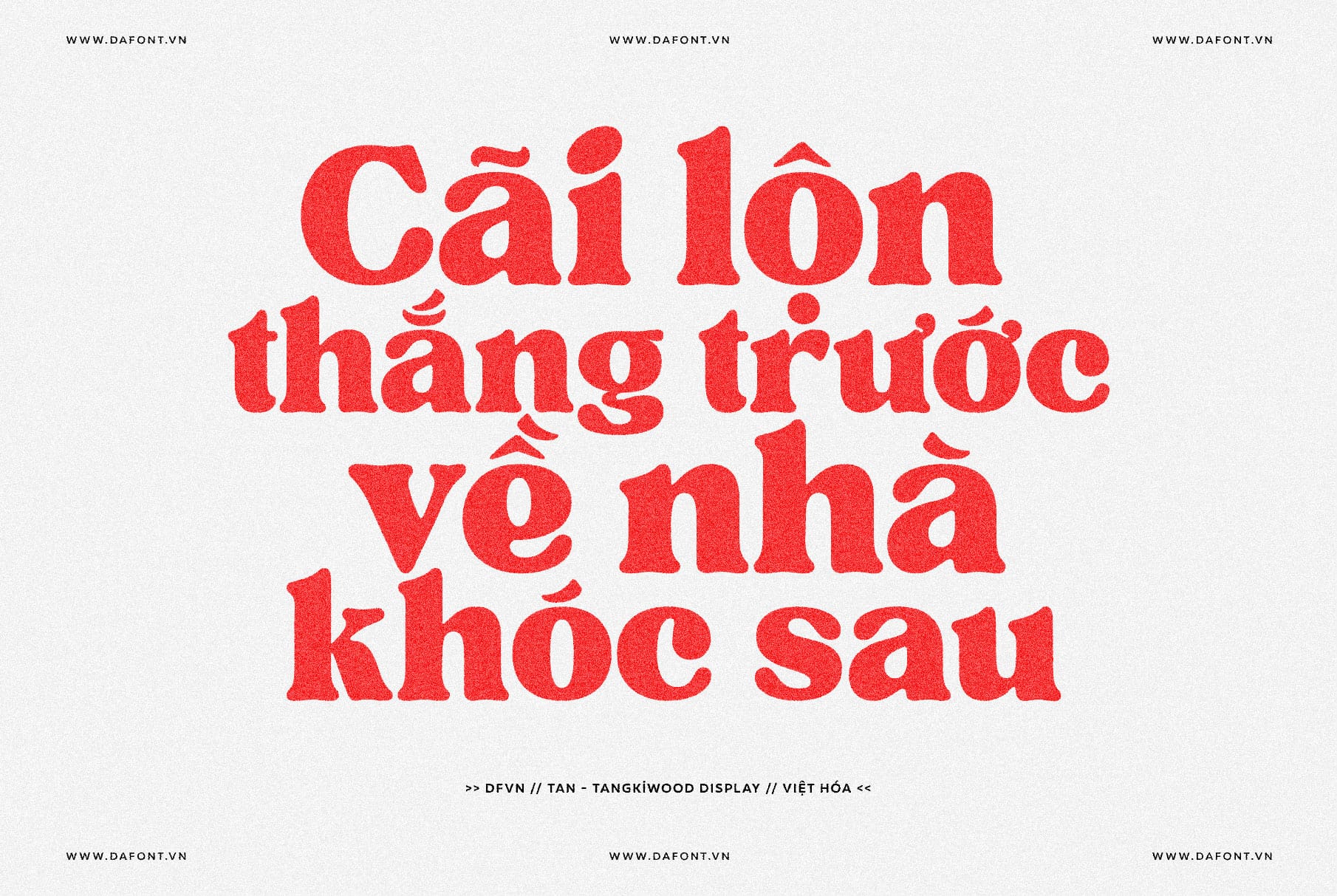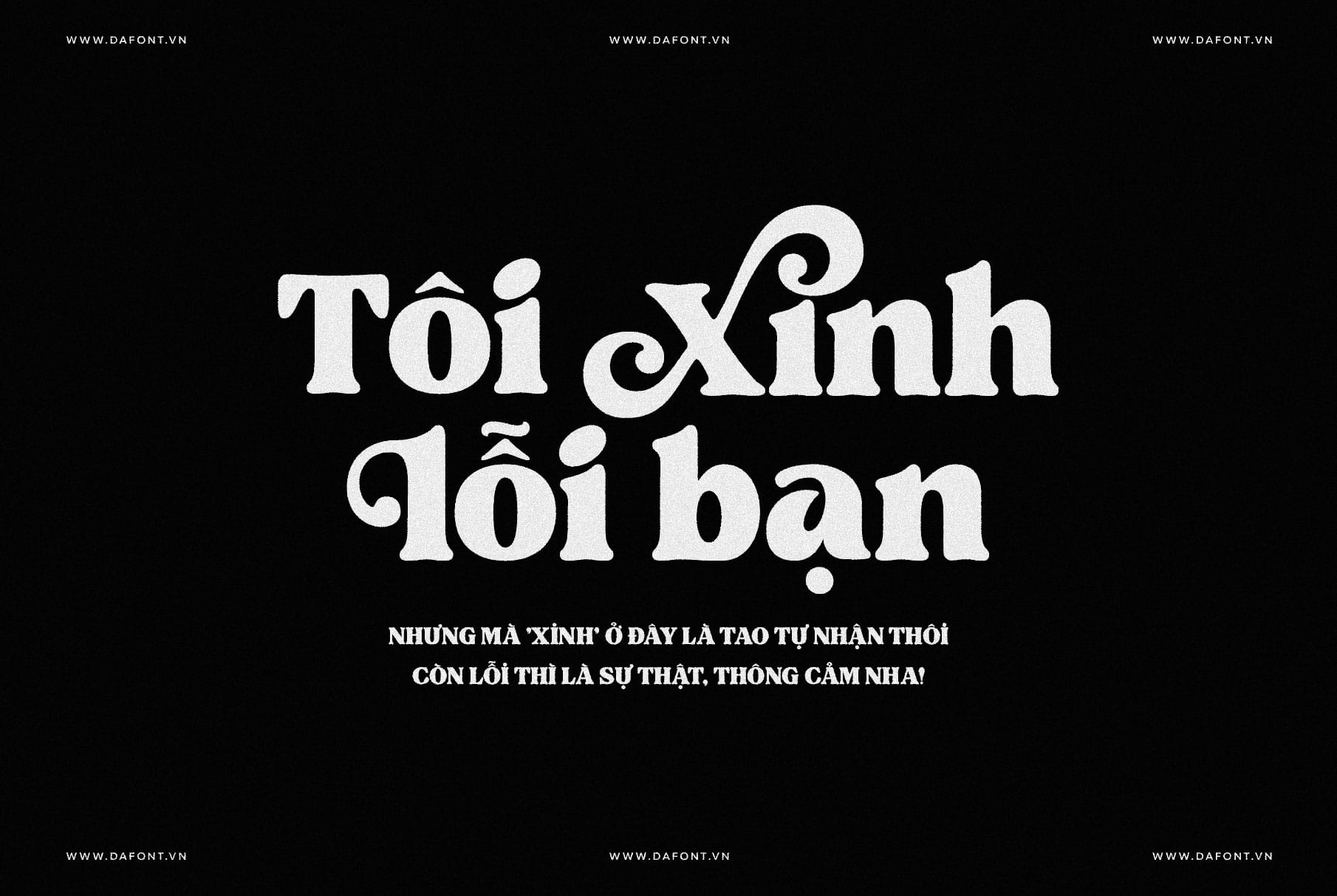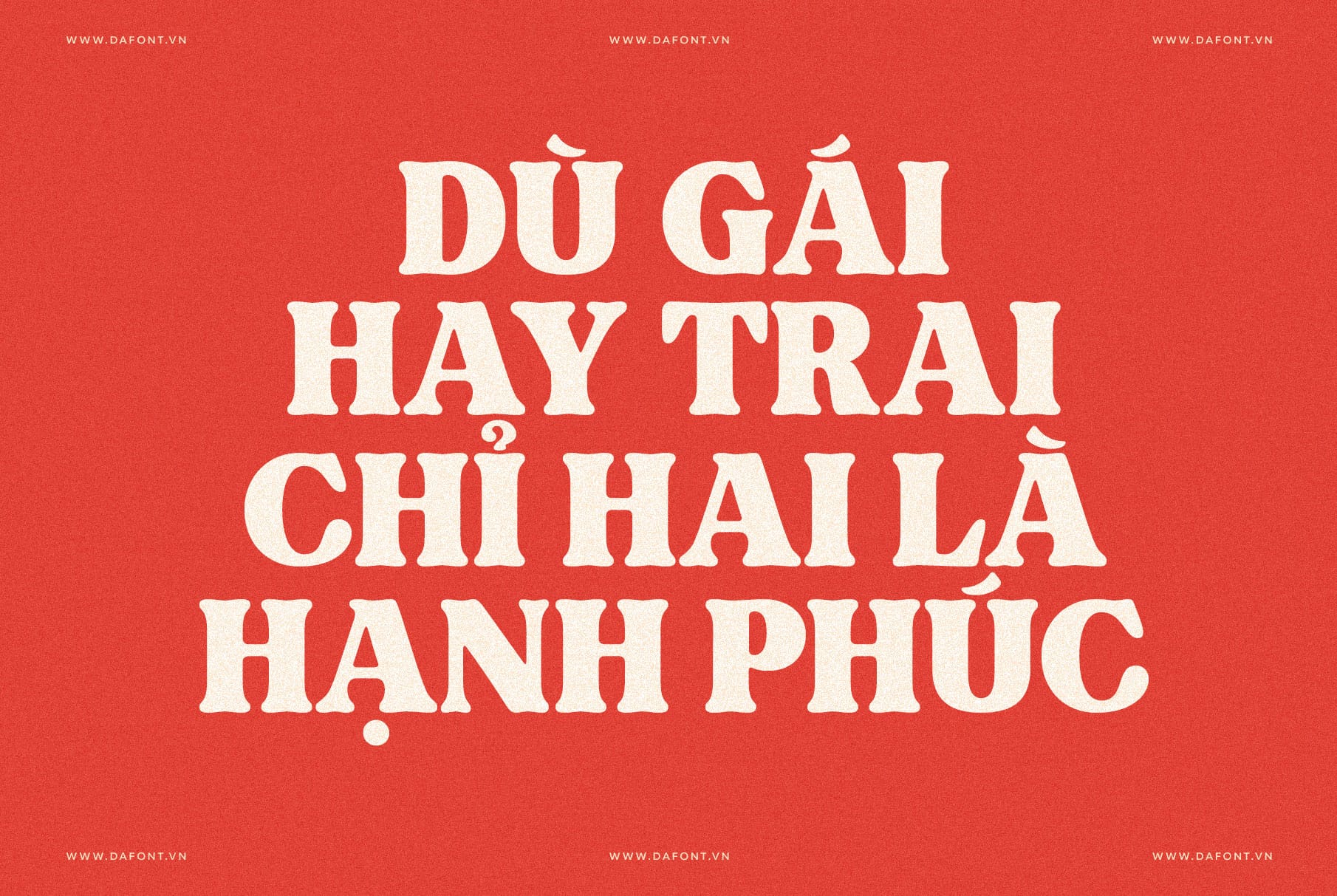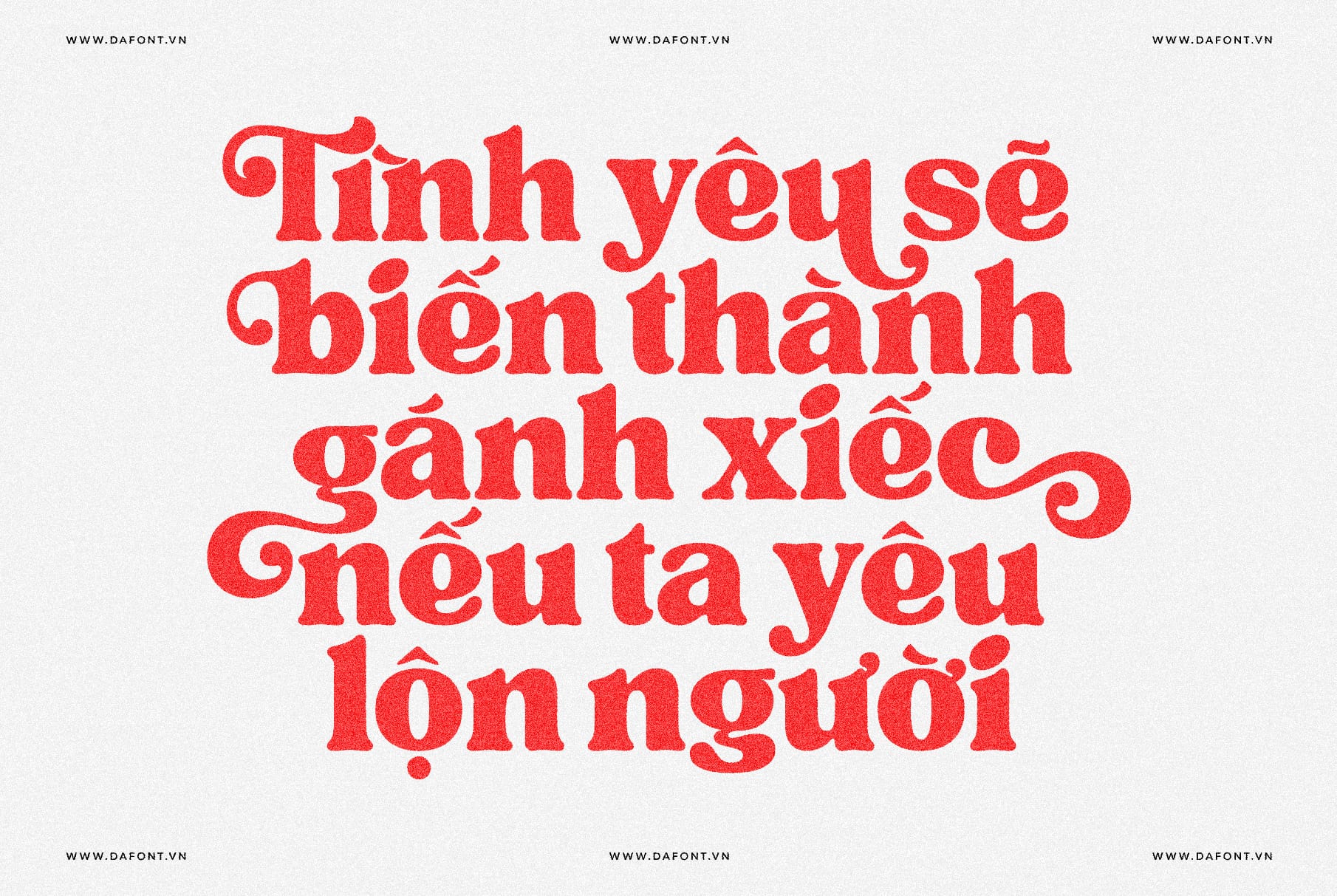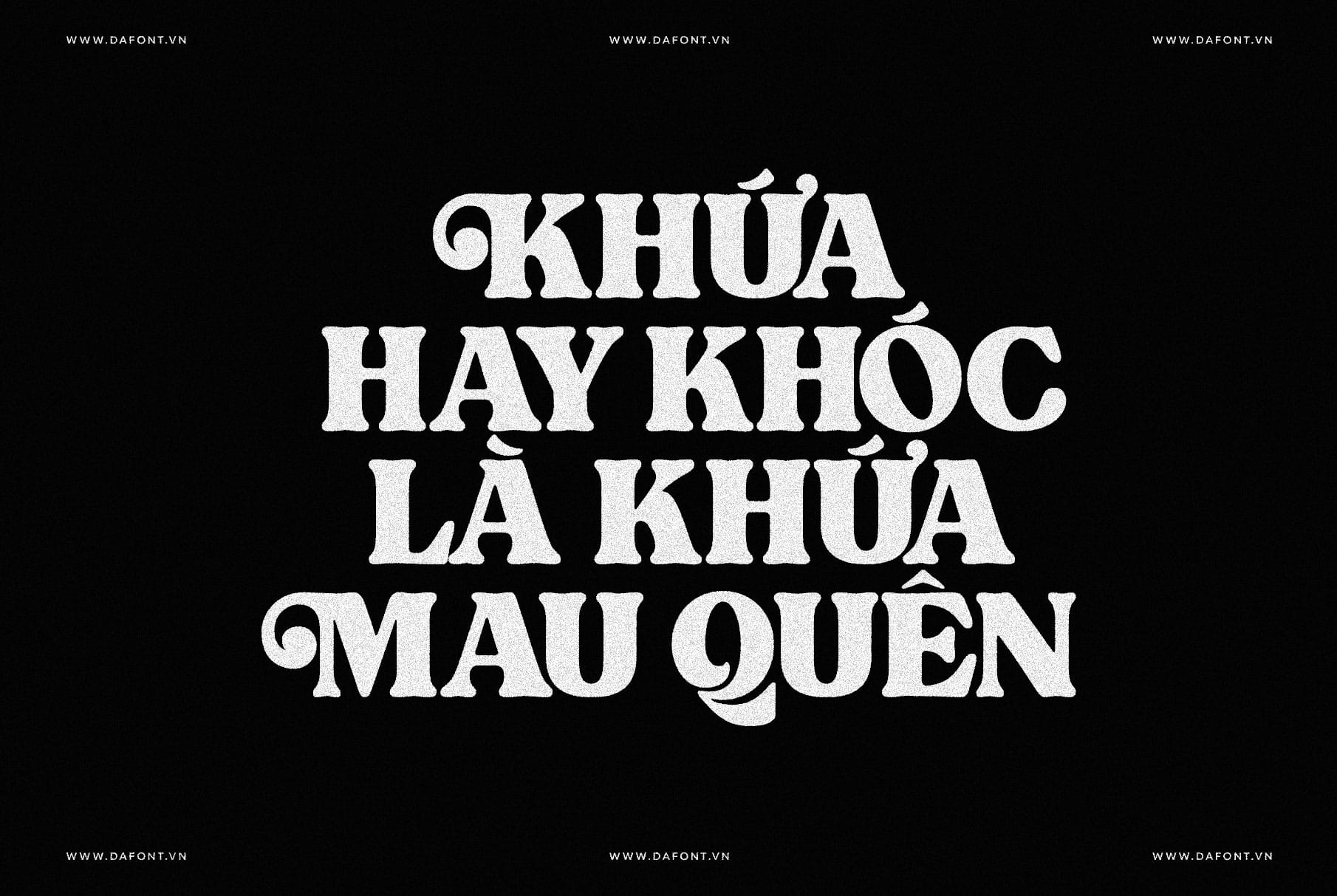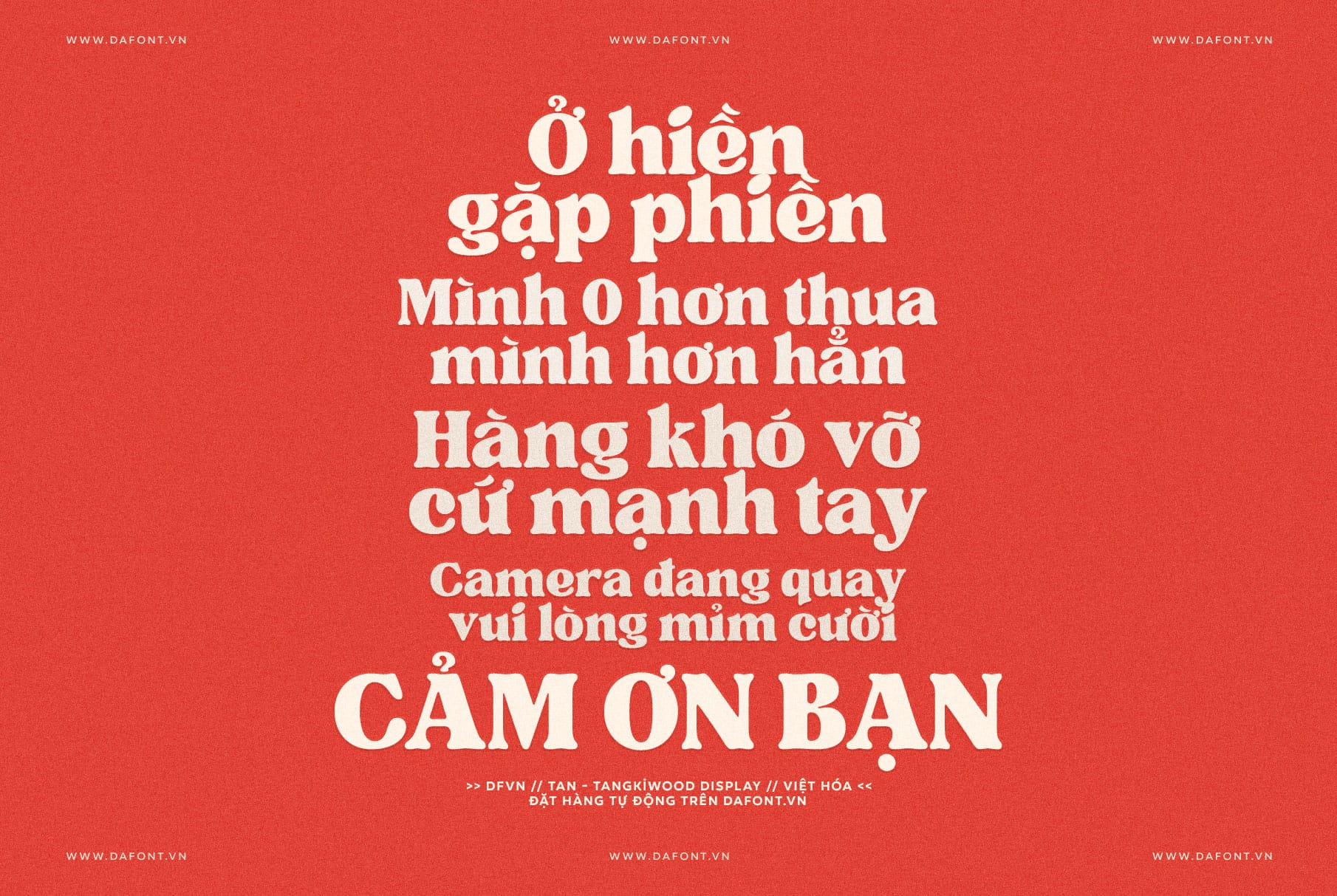
DFVN TAN – TANGKIWOOD
Phong cách retro đậm chất 70s cho thiết kế hiện đại
Nếu bạn đang tìm kiếm một font chữ có khả năng thể hiện đúng tinh thần của một thời đại hay một cảm xúc cụ thể cho thiết kế của bạn. DFVN TAN – TANGKIWOOD chính là một typeface dành cho bạn, mang đậm dấu ấn của thập niên 70 với vibe retro độc đáo, đồng thời sở hữu sự mạnh mẽ và vui tươi.
DFVN TAN – TANGKIWOOD – Đậm chất retro
Angkiwood là một display typeface với một độ đậm duy nhất, được thiết kế lấy cảm hứng từ phong cách thập niên 70. Với vibe đậm chất retro, font chữ này mang đến sự kết hợp hoàn hảo giữa sự táo bạo và vui nhộn, làm cho nó trở thành một serif typeface thú vị.
DFVN TAN – TANGKIWOOD không chỉ nổi bật với các đặc điểm thiết kế độc đáo mà còn cung cấp các alternates (ký tự thay thế) cho cả chữ hoa và chữ thường, giúp tăng thêm sự đa dạng và cá tính cho văn bản. Ngoài ra, với hơn 500 ký tự thay thế đã được Việt hóa và dễ dàng sử dụng bằng tính năng Opentype.
Ứng dụng lý tưởng của DFVN TAN – TANGKIWOOD
Với kiểu chữ hiển thị và cảm hứng cổ điển, Angkiwood phù hợp cho nhiều mục đích sử dụng:
• Tiêu đề và tựa đề: Làm nổi bật tiêu đề trên trang web, blog hoặc tạp chí với phong cách bắt mắt.
• Áp phích và tờ rơi: Hoàn hảo cho các sự kiện quảng bá, đặc biệt là những sự kiện mang chủ đề âm nhạc hoặc cổ điển.
• Thương hiệu và logo: Tạo ra những logo đáng nhớ cho các thương hiệu muốn gợi lên sự hoài niệm hoặc hình ảnh vui tươi.
• Thiết kế bao bì: Thêm nét quyến rũ cổ điển cho bao bì sản phẩm, đặc biệt trong ngành thực phẩm, đồ uống hoặc phong cách sống.
• Đồ họa mạng xã hội: Thu hút sự chú ý trên các nền tảng xã hội với văn bản ấn tượng và nổi bật.
Gợi ý sử dụng
Để DFVN TAN – TANGKIWOOD phát huy tối đa sức hút, hãy:
• Kết hợp với kiểu chữ đơn giản như Sans Serif để làm nội dung chính, giữ Angkiwood cho phần tiêu đề.
• Sử dụng bảng màu đậm chất thập niên 70 như cam, vàng hoặc nâu để tăng tính thẩm mỹ.
• Đảm bảo kích thước chữ đủ lớn khi dùng cho văn bản dài để duy trì khả năng đọc.
• Ngoài ra, kiểu chữ này cũng rất lý tưởng cho các đoạn văn ngắn, giúp chúng trở nên sinh động và bắt mắt hơn.
Kết Luận
DFVN TAN – TANGKIWOOD là một kiểu chữ hiển thị đa năng, mang đến sự vui nhộn và đậm chất thập niên 70 cho các thiết kế đương đại. Với độ đậm duy nhất, các ký tự thay thế độc đáo, nó mở ra vô số khả năng sáng tạo cho các nhà thiết kế.
Dù bạn đang thực hiện một dự án mang phong cách cổ điển hay muốn thêm nét tươi vui vào tác phẩm của mình, Angkiwood chắc chắn là một lựa chọn đáng cân nhắc. Hãy thử nghiệm và để sự sáng tạo của bạn bay xa với kiểu chữ độc đáo này!